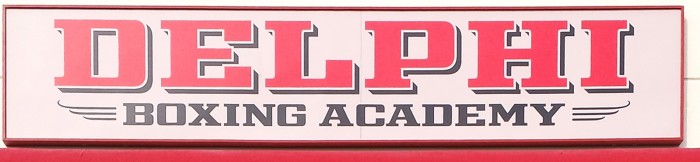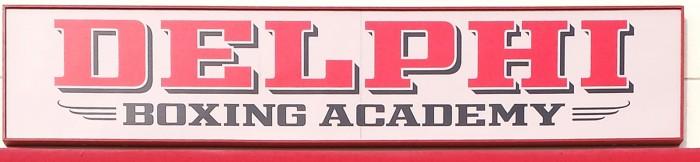
Suche diesen Boxfont in Sans Serif für Logo Rekunstruktion
ich bin auf der Suche nach dem Font auf diesem Bild. Nach langer Recherche vermute ich dahinter einen Custom-Font oder zumindest einen modifizierten. Eventuell existiert er aber auch schon als Zeichensatz. Für die Hilfe wäre ich super dankbar.